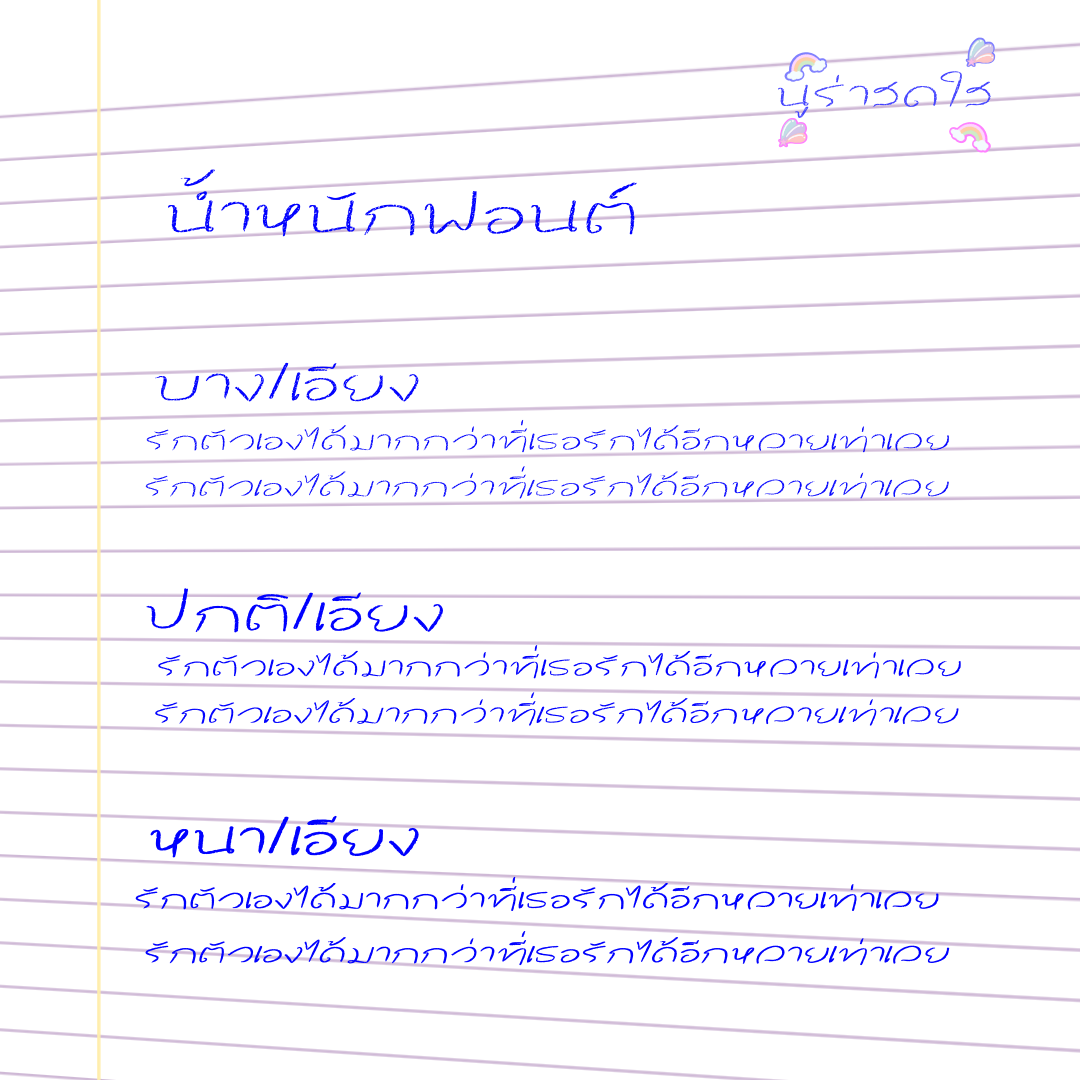
นูร่าสดใส (Nura sodsai)
ฟอนต์ลายมือไม่มีหัว เทคเจอร์เหมือนเขียนด้วยสีเทียน ฟอนต์มีด้วยกัน 6 น้ำหนัก คือ บาง ปกติ หนา เอียงบาง เอียงปกติ และเอียงหนา  นูร่าราดาเปิดให้ใช้ฟรีส่วนตัว น้ำหนักบาง และน้ำหนักหนาเอียงนะคะ